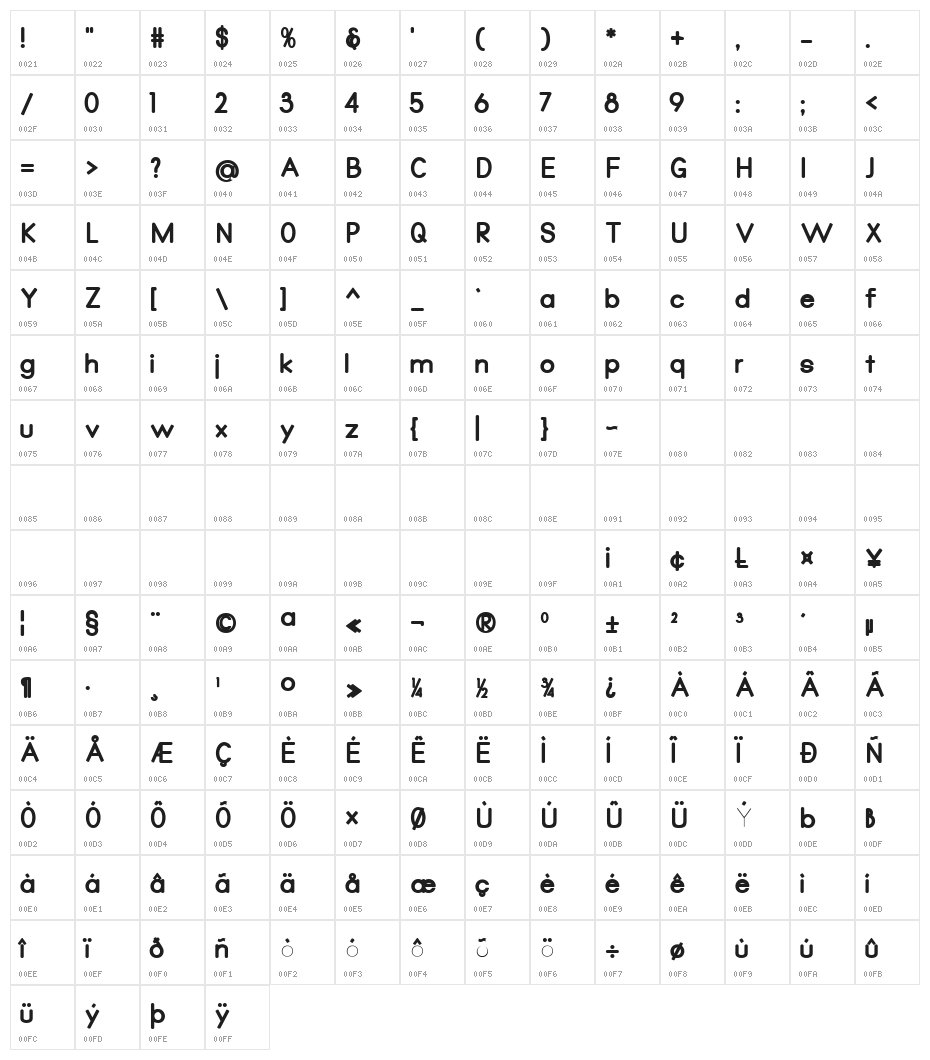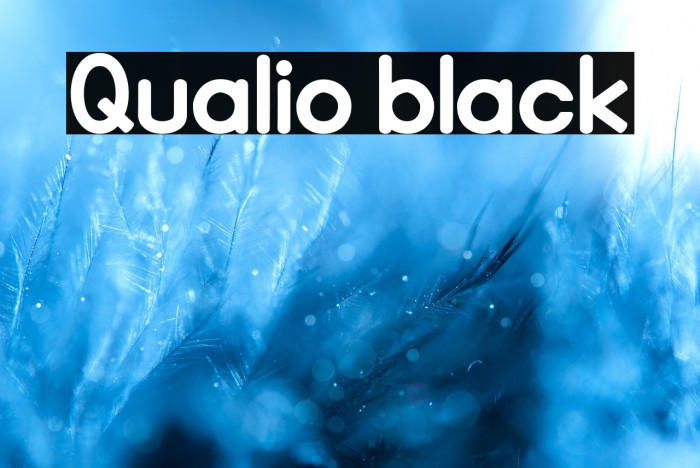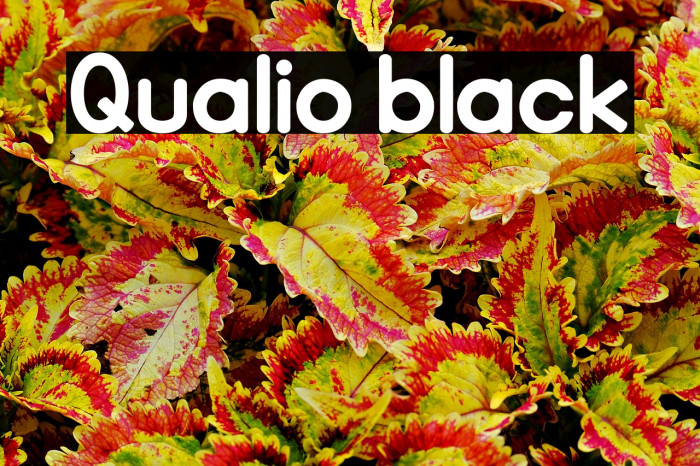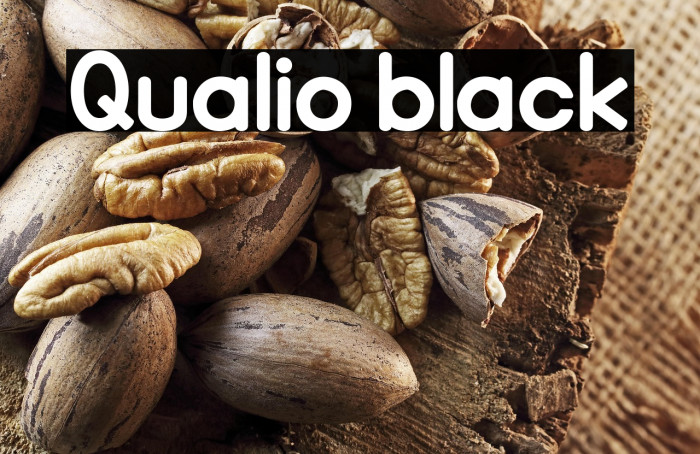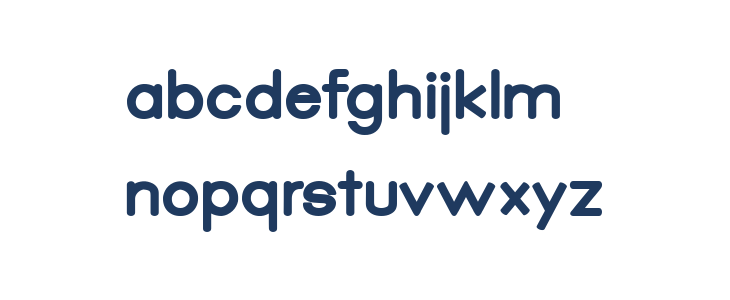
Qualio black Font
| Caso d'uso | Headlines, Logos, Digital interfaces |
| Progetti proposti | Ideal for branding, signage, packaging, and digital interfaces where a modern and approachable look is desired. |